![[Tải xuống] Bộ 4 font chữ đồng hồ điện tử digital cho thiết kế](https://cdn.s99.vn/blog/font-chu-dien-tu-1500x666.jpg)
Font chữ là một yếu tố quan trọng, ảnh hưởng trực tiếp đến sự thành công của bất kỳ sản phẩm thiết kế nào. Đặc biệt, với sự phát triển của công nghệ, font chữ điện tử đã trở thành lựa chọn không thể thiếu cho các nhà thiết kế. Trong bài viết này, chúng ta sẽ tìm hiểu chi tiết về font chữ điện tử, cách lựa chọn phù hợp và nguồn tải miễn phí dễ dàng.
Font chữ điện tử được tạo ra thông qua lập trình máy tính, khác biệt hoàn toàn so với các font chữ truyền thống viết tay. Điểm đặc trưng của font chữ điện tử là các đường nét thẳng, gãy gọn và góc cạnh, giống như những thanh que diêm được sắp xếp thành chữ.
Ví dụ điển hình của font chữ điện tử là các con số hiển thị trên đồng hồ điện tử hay còn gọi font chữ đồng hồ điện tử. Mặc dù thiết kế đơn giản, những font này vẫn mang lại vẻ cá tính và hiện đại, phù hợp với nhiều mục đích thiết kế khác nhau.
Font chữ điện tử có nguồn gốc từ các nước phát triển, nơi công nghệ và lập trình được ứng dụng mạnh mẽ vào thiết kế. Khi du nhập vào Việt Nam, những font này chưa được Việt hóa, gây khó khăn trong việc sử dụng cho các dự án tiếng Việt.
Nhờ sự sáng tạo và nỗ lực của các kỹ sư công nghệ trong nước, các font chữ điện tử đã được Việt hóa thành công. Điều này không chỉ giúp tăng tính ứng dụng mà còn mở rộng khả năng thiết kế của các nhà sáng tạo nội dung trong nước.
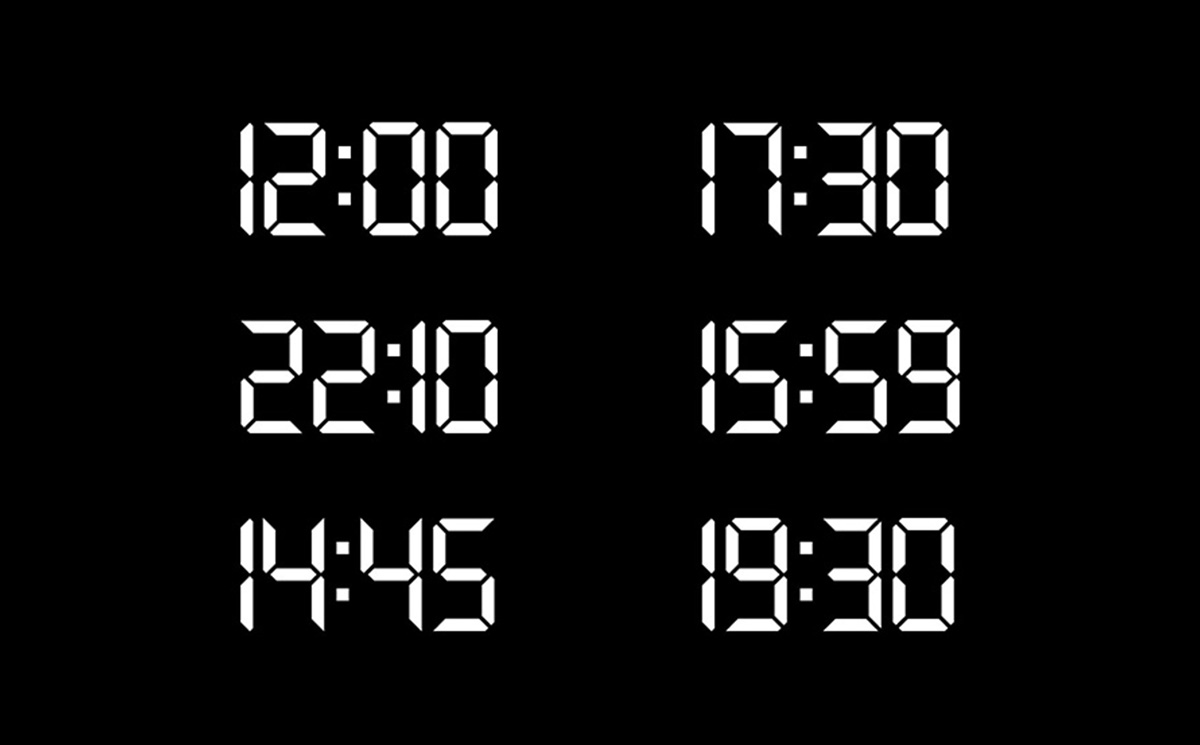
Font chữ điện tử không chỉ đẹp mà còn rất linh hoạt, phù hợp với nhiều lĩnh vực thiết kế:
Tính hiện đại: Các đường nét góc cạnh, cứng cáp mang đến vẻ hiện đại, phù hợp với các dự án công nghệ, game, và quảng cáo.
Đa dạng ứng dụng: Font chữ điện tử được sử dụng trong các poster, thiết kế website, giao diện ứng dụng, và cả trong sản xuất phim.
Dễ dàng tùy chỉnh: Với sự hỗ trợ của phần mềm thiết kế, các font chữ điện tử có thể được điều chỉnh để phù hợp với nhiều phong cách khác nhau.
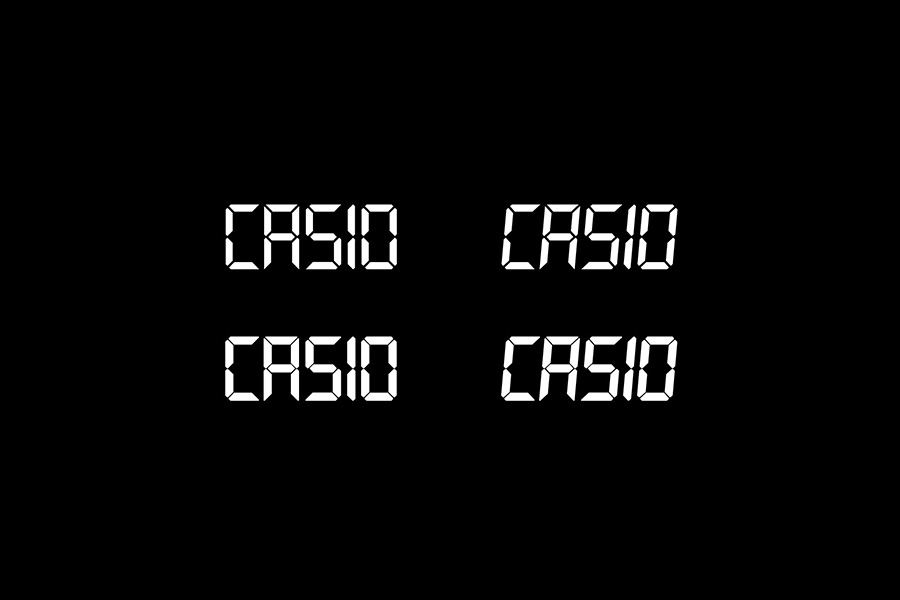
Lựa chọn font chữ điện tử phù hợp là bước quan trọng để tạo nên một thiết kế ấn tượng. Dưới đây là một số mẹo hữu ích:
Trước khi chọn font, hãy đảm bảo bạn hiểu rõ mục tiêu của dự án. Ví dụ, nếu bạn đang thiết kế cho một thương hiệu công nghệ, hãy chọn những font chữ mang tính hiện đại và chuyên nghiệp.
Font chủ đạo là phần nội dung chiếm nhiều không gian trong thiết kế, thường là văn bản chính. Đảm bảo font này dễ đọc, không quá phức tạp để tránh làm mất đi sự tập trung của người xem.
Kích cỡ chữ cần hài hòa với tổng thể thiết kế. Chữ quá lớn hoặc quá nhỏ đều có thể gây khó chịu cho người xem.
Khoảng cách giữa các ký tự và dòng cần được điều chỉnh hợp lý để đảm bảo tính thẩm mỹ và dễ đọc. Đây là yếu tố quan trọng để tránh làm người xem cảm thấy rối mắt.
Người thiết kế nên tận dụng khả năng cảm thụ của mình để lựa chọn font phù hợp. Hiểu rõ sản phẩm, dịch vụ và đối tượng mục tiêu sẽ giúp bạn đưa ra quyết định đúng đắn.
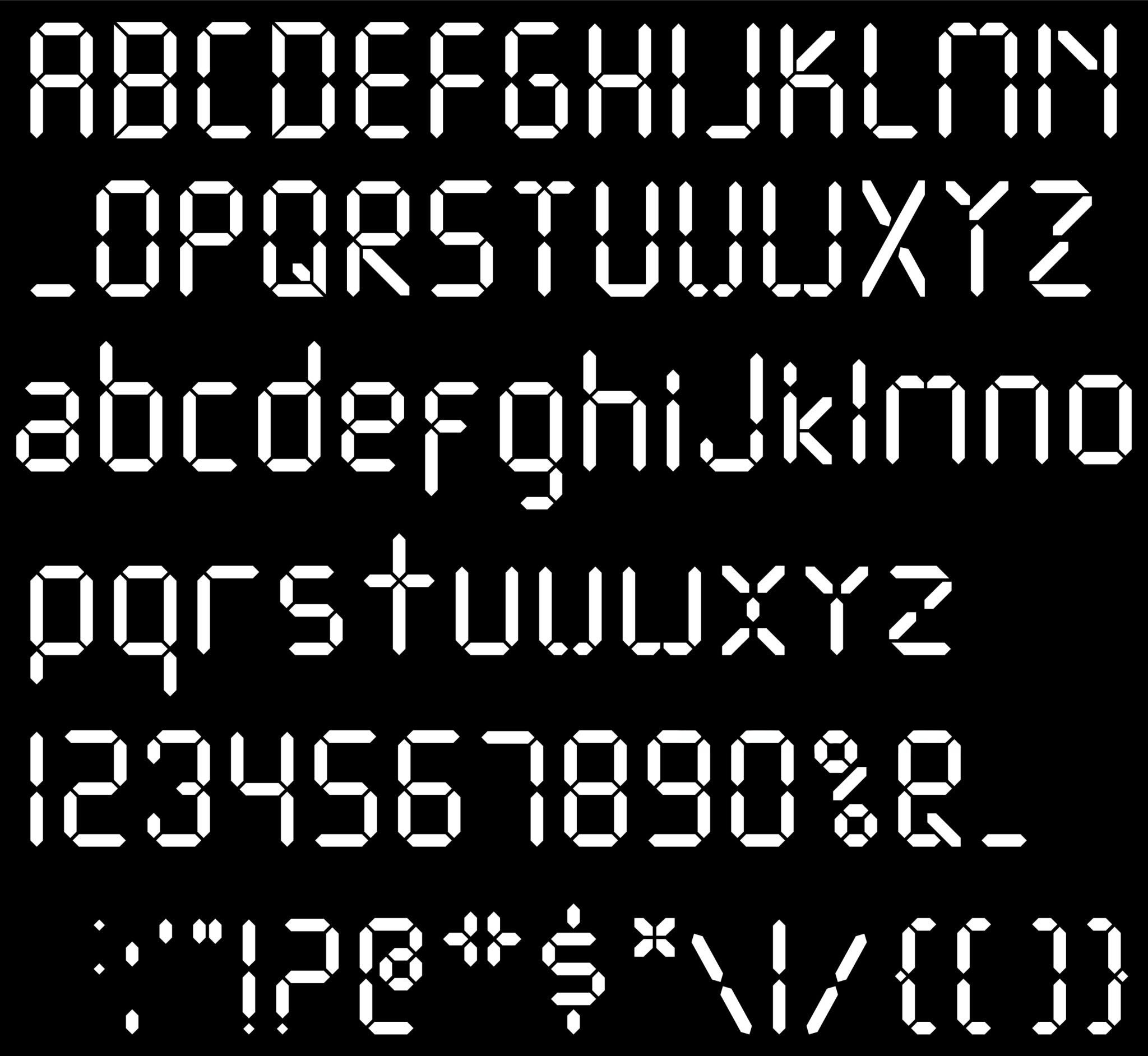
Font chữ điện tử được sử dụng rộng rãi trong nhiều lĩnh vực:
Thiết kế poster: Các font chữ góc cạnh, mạnh mẽ giúp tạo điểm nhấn trong các sự kiện hoặc sản phẩm công nghệ.
Giao diện ứng dụng: Độ rõ nét và hiện đại của font chữ điện tử rất phù hợp cho các giao diện app và website.
Sản xuất video: Font chữ điện tử thường được dùng để chèn tiêu đề, phụ đề trong các video quảng cáo và giới thiệu sản phẩm.
In ấn: Các thiết kế bao bì, nhãn mác sử dụng font chữ điện tử thường mang lại cảm giác công nghệ và chuyên nghiệp.
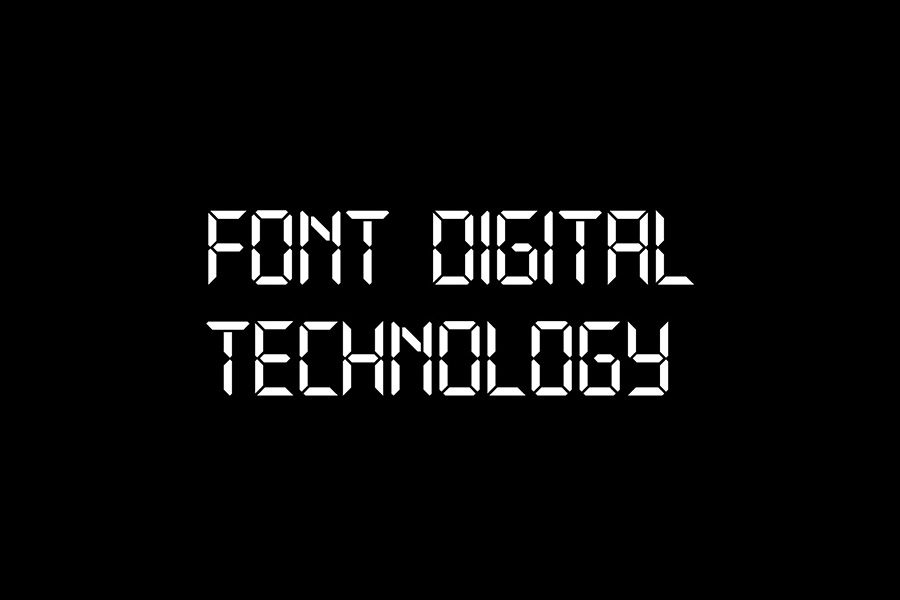
Font chữ điện tử không chỉ là một công cụ thiết kế mà còn là nguồn cảm hứng sáng tạo vô tận. Với các đặc điểm hiện đại, linh hoạt và dễ ứng dụng, font chữ điện tử đã trở thành lựa chọn hàng đầu của nhiều nhà thiết kế.